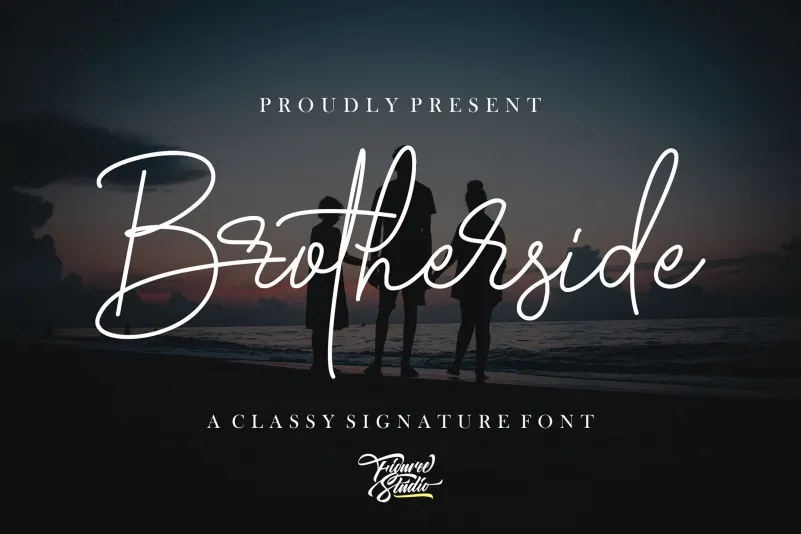
Esta página apresenta a Brotherside Signature Font, uma elegante fonte script desenvolvida para designers que buscam uma alternativa natural e delicada à escrita ao vivo. Através de seu design puramente manual, essa font oferece características naturais, tornando-a perfeita tanto para textos detalhados quanto para aplicações publicitárias, embalagens ou conteúdo social. Com um estilo elegante e uma ótima fluidez, a Brotherside Font é perfeitamente adequada para os designers que desejam incorporar um ar delicado às suas criações gráficas modernas. Seja em letras grandes ou menores, essa fonte pode dar um toque único à sua peça, transformando seu design de um nível elevado. Não importa o uso, a Brotherside Font será uma ótima escolha para aqueles que buscam tanto qualidade quanto simplicidade e elegância em suas criações.